10 tipografías vintage para incorporar a tus diseños
Cuando ideamos un diseño, en los elementos que pensamos primero generalmente son en las imágenes, en los colores que tendrá o en el texto que lo acompañará. La tipografía no es siempre de las primeras cosas que vienen a la mente de un diseñador cuando empieza a crear. Pero es uno de los elementos imprescindibles para que un diseño tenga éxito. Sobre todo, porque en muchos casos puedes elegir el estilo de tipo de letra que mejor combine con el estilo del resto del diseño. Así, puedes elegir entre tipografías vintage, modernas, elegantes, más informales e incluso con elementos gráficos.
Quizá los diseños más particulares son los que tienen un cierto aire retro o vintage. En ellos no puede utilizarse cualquier tipografía, ya que si no se emplea una con un cierto aire antiguo o nostálgico, el resultado puede ser desastroso. Por eso conviene en estos casos utilizar un tipo de letra que sugiera que los textos del diseño tienen un aire antiguo.
Podrás encontrar tipografías vintage para tus diseños en la práctica totalidad de programas de diseño y maquetación que emplees para crearlo. Pero si aun así no te parecen suficientes, siempre hay otras tipografías de estilo retro o vintage que puedes incorporar a tus diseños, con solo descargarlas e instalarlas.
Tipografías vintage: Roman Font VII, con caracteres que denotan antigüedad
En la actualidad hay muchas tipografías vintage caracterizadas porque sus letras tienen el mismo aspecto de la caligrafía que se practicaba hace varias décadas. O incluso hace varios siglos. Por ejemplo, con letras de aspecto parecido a la que tenían las que utilizaban los romanos.
Una de ellas es la Roman Font VII, que está inspirada directamente por las letras que empleaban los antiguos romanos. Es el principal motivo de que esta tipografía solo tenga letras mayúsculas. Otra de sus particularidades reside en que en ella los números se representan con letras, como sucede con los números romanos. Es libre para uso personal.
Tipografía Carolingia
Algunos siglos después, en la Edad Media, se desarrolló en los monasterios un tipo de letra conocida como Carolingia. Esta ha servido de base para el desarrollo de una tipografía del mismo nombre y formato TrueType, que añadirá a tus diseños un aire de manuscrito medieval. Se trata de un tipo de letra gratuito para uso personal y comercial.
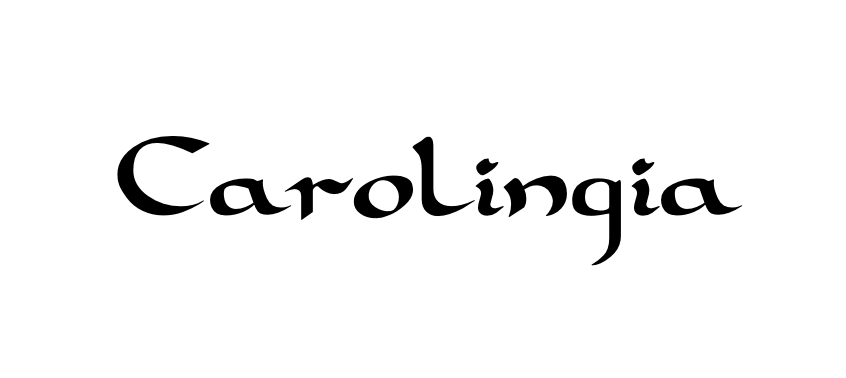
Clarendon y su derivada Munson
Unos siglos más tarde, ya en el siglo XIX comenzaron a utilizarse fuentes con grandes serifas de tipo egipcio. El diseño de fuentes de estilo vintage se ha inspirado con frecuencia en los tipos de letra de dicho siglo, como muestran tipografías como Clarendon, nacida allá por la década de los 40 del siglo XIX y con un estilo que recuerda a las letras de dicha época. Se puede encontrar en todo tipo de programas y herramientas, e incluso en el sistema operativo Windows. De ella deriva la Munson, una fuente OpenType gratuita y caracterizada también por dar gran protagonismo a las serifas.
Tipografía modernista: Nickelodeon NF
Pocas décadas más tarde llegó el movimiento modernista, que también tuvo su influencia en los tipos de letra. Tanto en la época como en diseños de tipografía vintage posteriores que se utilizan para dar un aspecto vintage y nostálgico a muchos diseños con estilo claramente inspirado por el modernismo. Sobre todo, en el ámbito de la publicidad. Un ejemplo es la tipografía Nickelodeon NF, una fuente TrueType que destaca por su sobriedad. Es gratis para uso personal y comercial.
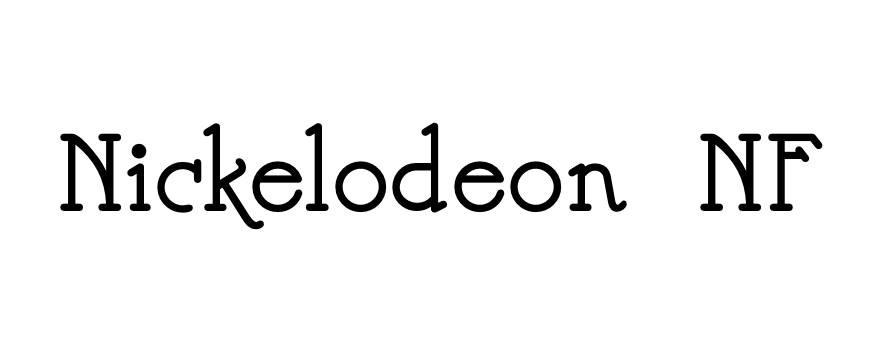
Tipografías inspiradas en logos y carteles del siglo XX: Rio Grande
A pesar de que hasta el siglo XX se desarrollaron bastantes tipografías famosas, el siglo pasado es quizá el que más variedad de estilos diferentes de tipografías vintage ha visto nacer. La llegada de la televisión y el auge del diseño gráfico y de la publicidad auparon muchos tipos de letra, que nos resultan muy familiares a la vez que evocan tiempos pasados. Es lo que sucede cuando vemos fuentes como Rio Grande, gratuita para uso personal. Está inspirada en los carteles y los títulos de crédito y apertura de no pocas películas del Oeste americano de mediados del siglo pasado.
Metropolis: una tipografía años 20
Pero si lo que prefieres es dar un estilo años 20 a tus diseños, nada mejor que una tipografía vintage inspirada en los caracteres cuyo estilo estaba más en boga en publicidad y cartelería en dicha década del siglo pasado. Por ejemplo, la Metropolis, caracterizada por el uso de las líneas rectas y un elevado nivel de sobriedad. Se trata de un tipo de letra muy elegante, que está pensado sobre todo para titulares y diseño de logos sencillos. Es ‘open source’ y puede utilizarse gratis para uso personal y comercial.
Una tipografía retro 80: Barista Script
Si lo que te gusta son las tipografías cuyas letras parezcan escritas a mano y que se enlacen unas con otras como en la escritura a mano, la Barista Script, OpenType, puede ser una tipografía vintage adecuada para diseños con un cierto toque años 80. Es gratuita y muy apropiada para logotipos que quieran tener un cierto aire de frescura, y simulen la escritura manual, como hemos comentado.